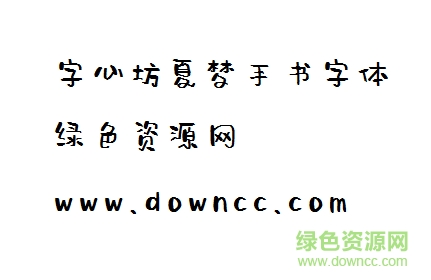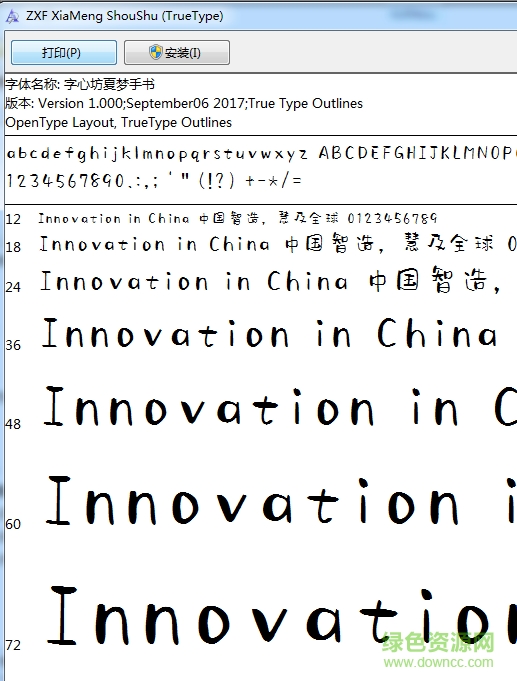
字心坊夏夢手書字體是一款好看的手寫字體,該字體盡顯清新可愛的萌萌噠心情,整體給人非常舒服的感覺,深受廣大年輕人喜愛,綠色資源網(wǎng)為您提供免費字體下載!
字心坊夏夢手書是一款應用于藝術設計方面的簡體中文字體,該字體筆畫粗壯,尾部的甩尾有力且有豐富的筆觸細節(jié),大字效果突出且引人注目;并且最大程度還原作者書寫字形,細節(jié)表現(xiàn)完整,且字庫完整,可以廣泛應用于名片設計、新聞媒體、宣傳海報、ppt、影視制作以及內容用字等領域。
簡約、小清新、時尚、手寫風、有趣!